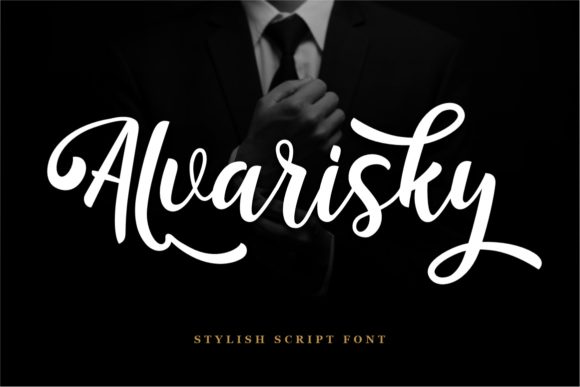
Creativefabrica Alvarisky Font
[Creativefabrica] Alvarisky Font
Альвариски - уникальный рукописный шрифт.
Неважно, используете ли вы его для ремесел, цифрового дизайна, презентаций или поздравительных открыток - он идеален!